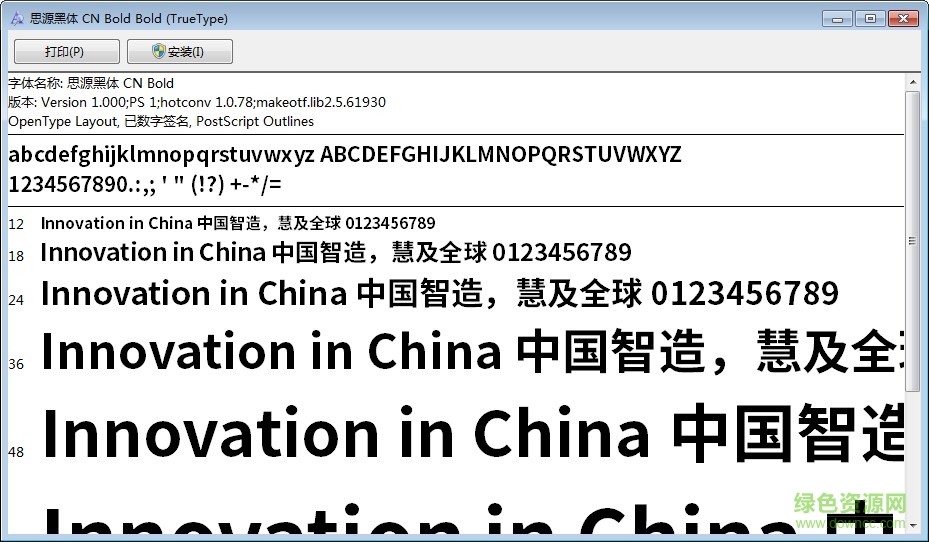
思源雅黑簡體中文版
思源雅黑
思源雅黑字體簡介:
該款字體是由Google和Adobe合作開發(fā)的。Google將其命名為Noto SansCJK,作為Google的Noto字體家族的成員。Adobe則命名為Source Han Sans,作為Adobe的Source字體家族的一員。Adobe擁有字體設(shè)計(jì)的版權(quán)。發(fā)布的字體文件則可以不受限制的免費(fèi)使用。這些字體文件使用Apache許可證版本。